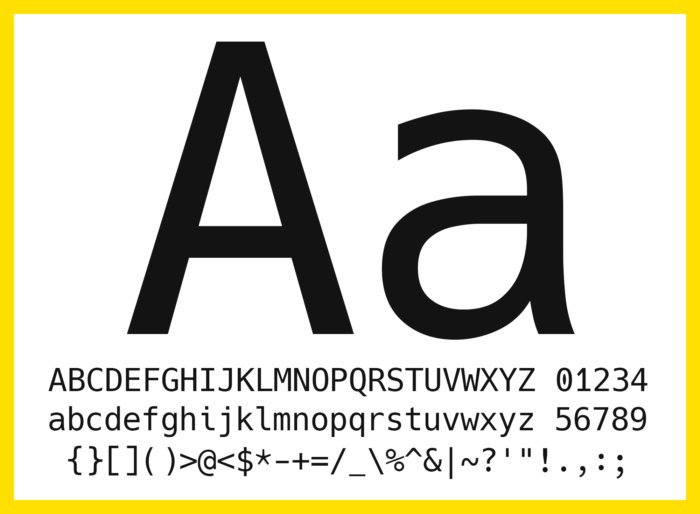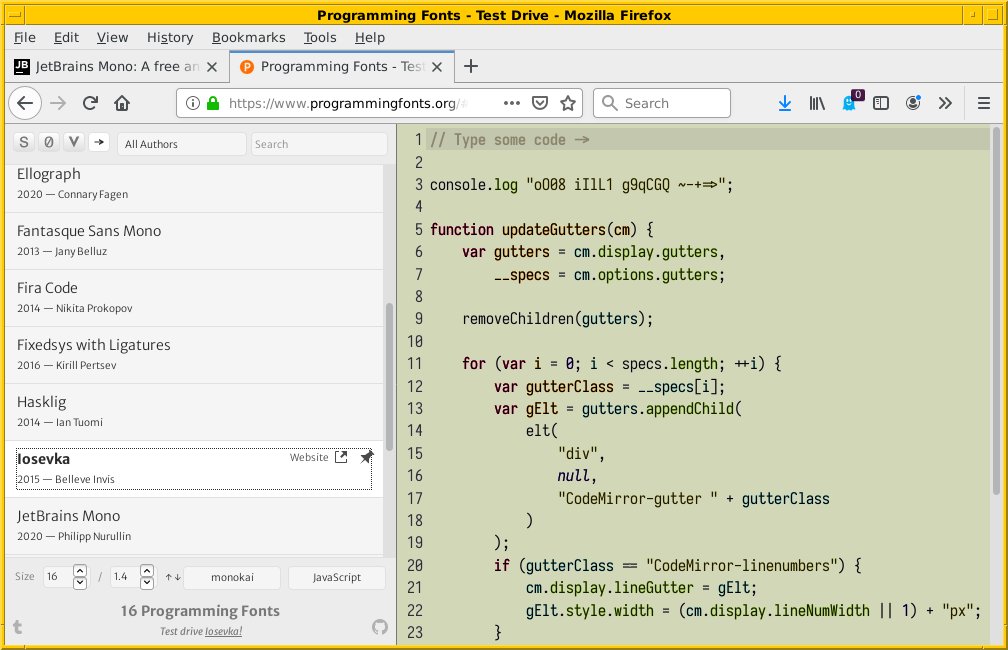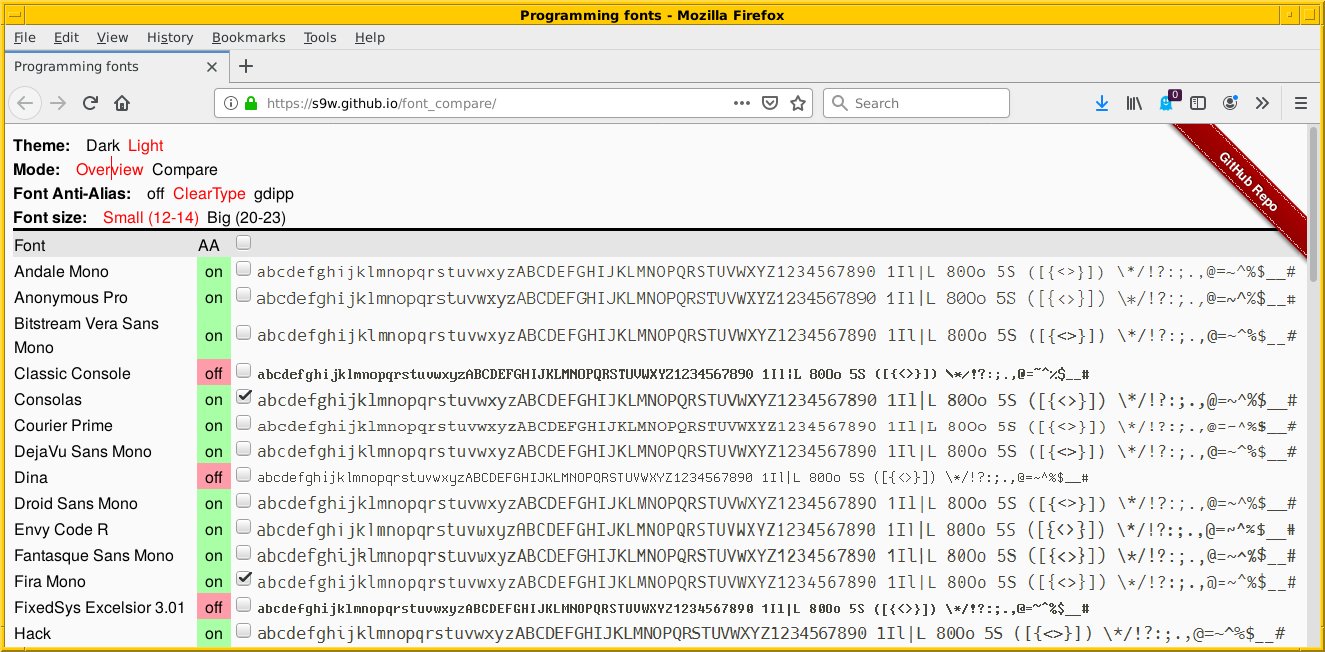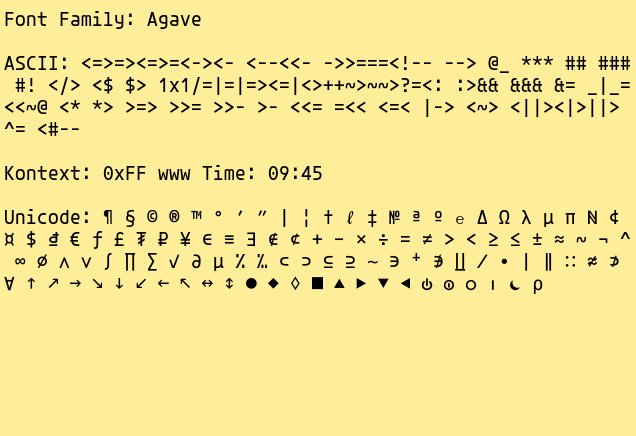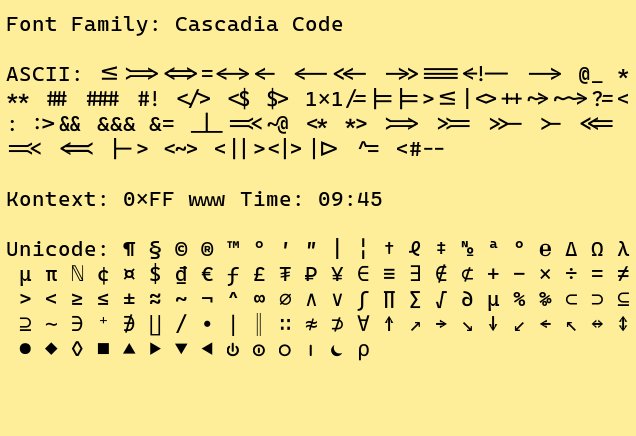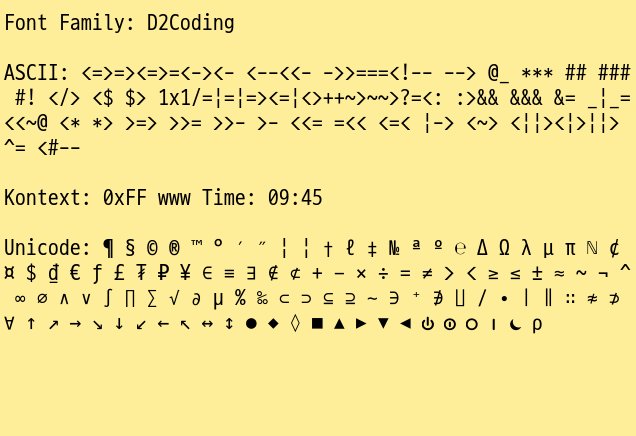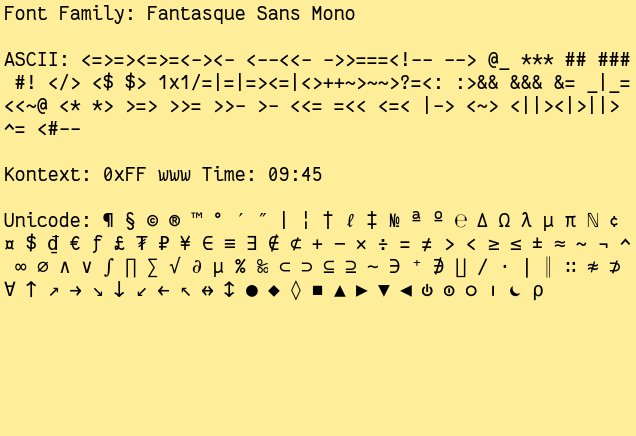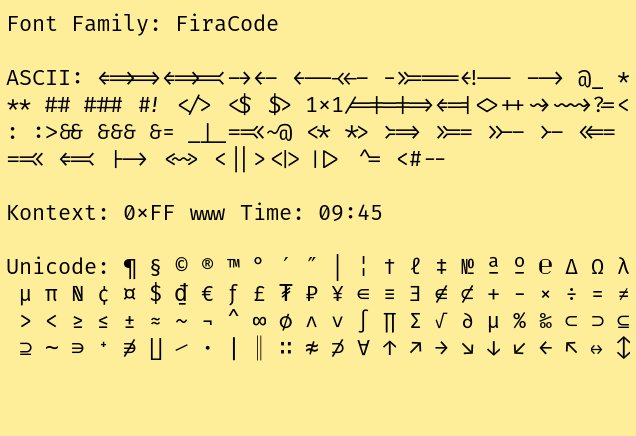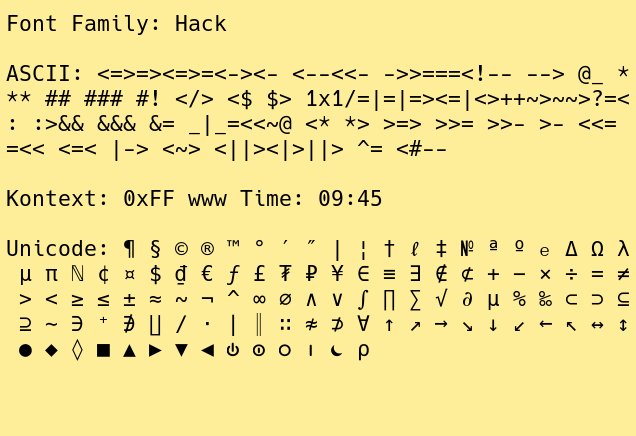
10 optimale Fonts für Programmierer
Form follows function
Die zur Darstellung verwendete Schriftart hat direkte Auswirkungen auf die Lesbarkeit von Code. Wir stellen 10 optimale Fonts für Programmierer vor.
Schriftarten und deren Lesbarkeit bestimmen, wie gut ein Rezipient die Inhalte eines Texts oder Schriftzugs aufnimmt. Neben der Größe der Zeichen spielt dabei deren Gestaltung eine besondere Rolle. Fonts transportieren bereits über ihr Aussehen eine Nachricht. Sie stellen beispielsweise den Bezug zu einer Zeitepoche, einem Ereignis, einer Branche oder einer Stimmung her [1].
Entwickler haben spezifische Anforderungen an Schriftarten für den Programmcode. Hier geht es nicht um das Erfassen von Inhalten im Fließtext oder das Üben von Schönschrift, sondern um eine klare Unterscheidbarkeit und Erfassbarkeit einzelner Zeichen in kurzer Zeit. Das betrifft besonders aussehende Lettern und Ziffern [2].
Kommt dieser Aspekt zu kurz, besteht die Gefahr, dass Sie wegen einer unpassenden Schriftart Tipp- oder Programmfehler im Code gar nicht, eher zufällig oder nur mit viel Aufwand entdecken. Die Tabelle Ähnliche Zeichen listet die Zeichen auf, bei denen Verwechslungsgefahr besteht.
Zeichengruppe
Ähnliche Zeichen
Null und O
O o 0
Eins, I, und L
1 I i L l
Fünf und S
5 S s
Zwei und Z
2 Z z
G und Q
g q
6, G und b
6 G b
Klammern
( { [ ] } )
Hochkommas
' ` "
Auf dem Bildschirm eignen sich zum Programmieren serifenlose [4], nichtproportionale Schriftarten am besten [3]. Serifenlos deswegen, da sich solche Fonts auf dem Bildschirm einfacher erfassen lassen. Nichtproportional heißt, dass alle Zeichen die gleiche Breite aufweisen, egal, ob es sich um ein breites Zeichen wie das W oder ein schmales Zeichen wie das l handelt – vereinfacht ausgedrückt: eine deutlich hübschere Variante der ehrwürdigen Schreibmaschinenschrift.
Was bringen diese Eigenschaften in der Praxis? Damit erreichen Sie mehr Übersichtlichkeit, insbesondere bei Funktionen und Datenstrukturen wie Listen und Arrays, wo Sie mit Einrückungen arbeiten. Abbildung 1 stellt das exemplarisch anhand der Definition einer Liste in Python dar. Verwendet wurden hier Fira Code Regular als nichtproportionale, serifenlose Schriftart (oben) und Bitstream Charter Regular als proportionale, serifenbehaftete Schriftart (unten). Die Darstellung zeigt eindeutig, dass sich proportionale Fonts für die Darstellung von Programmcode nur bedingt eignen.
Abbildung 1: Ein Schnipsel Programmcode mit nichtproportionaler und proportionaler Schriftart.
Einrückungen nehmen bei nichtproportionalen Schriftarten stets gleich viel Platz ein. Das sehen Sie insbesondere bei If-Then-Else-Blöcken oder gleichmäßig untereinander angeordneten Funktionen. Abbildung 2 zeigt das in der Programmiersprache Python mit der Schriftart B612 Mono.
Abbildung 2: Ein If-Then-Else-Block in der Monospace-Schriftart B612 Mono.
Weitverbreitete Fonts wie Courier und DejaVu Mono lassen sich gut für Programmcode einsetzen, patzen aber bei den zueinander ähnlichen Zeichen aus der Tabelle Ähnliche Zeichen. Das trifft ärgerlicherweise auch für die ansonsten sehr schön gestaltete Schriftart B612 Mono [5] zu. Sie wurde für die Darstellung im Cockpit von Flugzeugen entwickelt. Wie die Matrix in Abbildung 3 demonstriert, unterscheiden sich in diesem Font die drei Zeichen O (großes O), o (kleines o) und 0 (null) nicht eindeutig genug voneinander. Dasselbe gilt für runde und eckige Klammern (() und []), die beispielsweise bei Ausdrücken der Form print(liste[index]) einen aufmerksamen Blick fürs Detail erfordern.
Abbildung 3: Die Glyphen der Schriftart B612 Mono.
Daher rücken wir stattdessen Schriftarten in den Mittelpunkt, deren Zeichen so gestaltet sind, dass es einfach von vornherein nicht zu Verwechslungen kommen kann. Eine weitere Anforderung: Die nichtproportionalen Schriftarten müssen über spezielle Ligaturen für Programmierer verfügen. Als Ligatur bezeichnet man in der Typografie die Verschmelzung zweier oder mehrerer Einzelbuchstaben zu einer Glyphe, sprich: zu einem Schriftzeichen. Das soll optische Lücken zwischen Buchstaben verhindern. Solche Ligaturen kommen beispielsweise für die Kombinationen fi, fl und ff infrage.
Passende Schriftarten
Als langjährigen Debian-Anwendern gilt der erster Blick der Autoren den Font-Paketen aus den Repositories dieser Distribution. Ein hübscher Nebeneffekt: Die Schriftarten stehen allesamt unter einer freien Lizenz. Die Tabelle Nichtproportionale Fonts listet die entsprechenden Fonts alphabetisch aufsteigend samt zugehörigem Debian-Paket auf. Alle zehn Schriften entsprechen den festgelegten Kriterien.
Glossar
Serifenlos
Als Serife bezeichnet man in der Typografie eine kurze dünne Querlinie auf den Strichenden von Buchstaben und Zeichen.